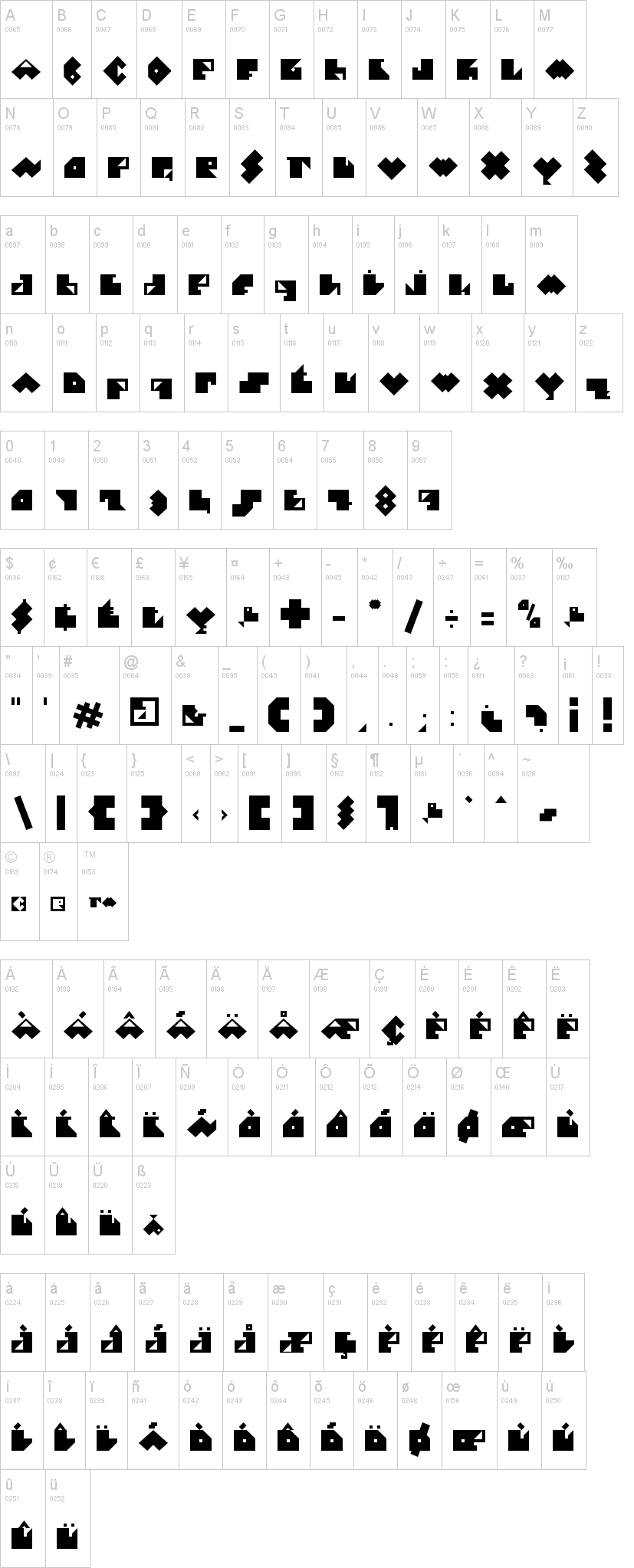
Note of the authorEsta tipografía experimental esta construida en su gran mayoría con las 3 piezas del imagotipo de mi logo: el pececito, un diseño geométrico y minimalista.
Para la mayoría de las letras uso exclusivamente estos 3 elementos ó 2. Juego con la resta y la suma, con el positivo y el negativo para conseguir la construcción de todas las letras.
En algunos casos duplico alguna de estas formas para conseguir que la tipografía disponga del mayor número de glifos.